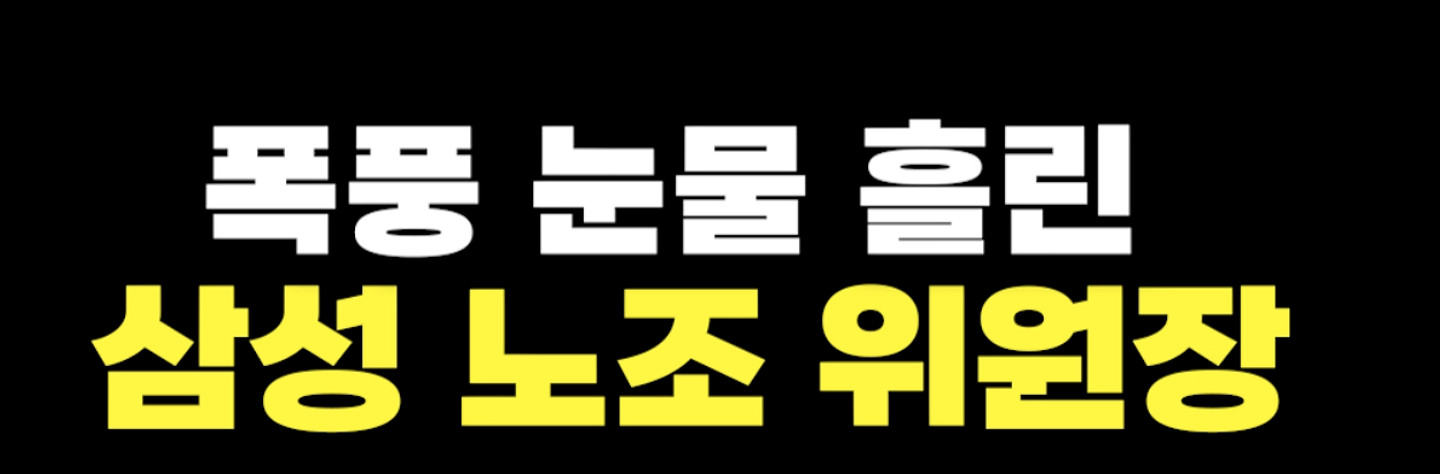
이름 부분이랑 아래 대화 폰트 둘 다 알고 싶습니다
10월, 공주에 무슨일이? 폰트가 궁금합니다. 스와시 스타일의 서체를 다 찾아봤는데 동일한 서체를 못 찾겠어서 도움 요청드립니다.
하얀 바탕안에 있는 폰트를 찾아주세요
무슨 폰트일까요???
바로 채택!! 이 영문폰트 Awazero에서 만든 타이포그래피인데 폰트 다운 파일로는 없어서 비슷한걸로 궁금합니다! 절단부분이 수평수직인 폰트였으면 좋겠습니다! 서체의 연결부에 액체 같은 곡선은 없어도 됩니다!
영어 정말 알고싶어요
한우돈 폰트 무슨폰트일까요?
이 글씨체 뭔지 아시는 분?ㅜ
너무 궁금합니다ㅜㅜ
꼬꼬바베큐 폰트 뭐에요??
어떤 영문 서체일까요?
진국정 폰트정보 알수있을까요 비슷한거라도 ㅠㅠ
요 폰트 무슨 폰트인가요오...?
이 폰트좀 찾아주세요 ㅠ 비슷한거라도 상업적무료로 쓸수있는 폰트가 있을까요?ㅠㅠㅠㅠ
혹시 이 폰트 아시는 분 있나요?
각별님 예전 영상에 나왔던(DIA TV 이적 초기) 폰트인데 무슨 폰트인지 궁금합니다
이거는 수분 꽉 채워주는 미스트 ㅎㅎ 이 폰트 도대체 정체가 뭐죠 ㅜㅜㅜㅜ 아시는 분